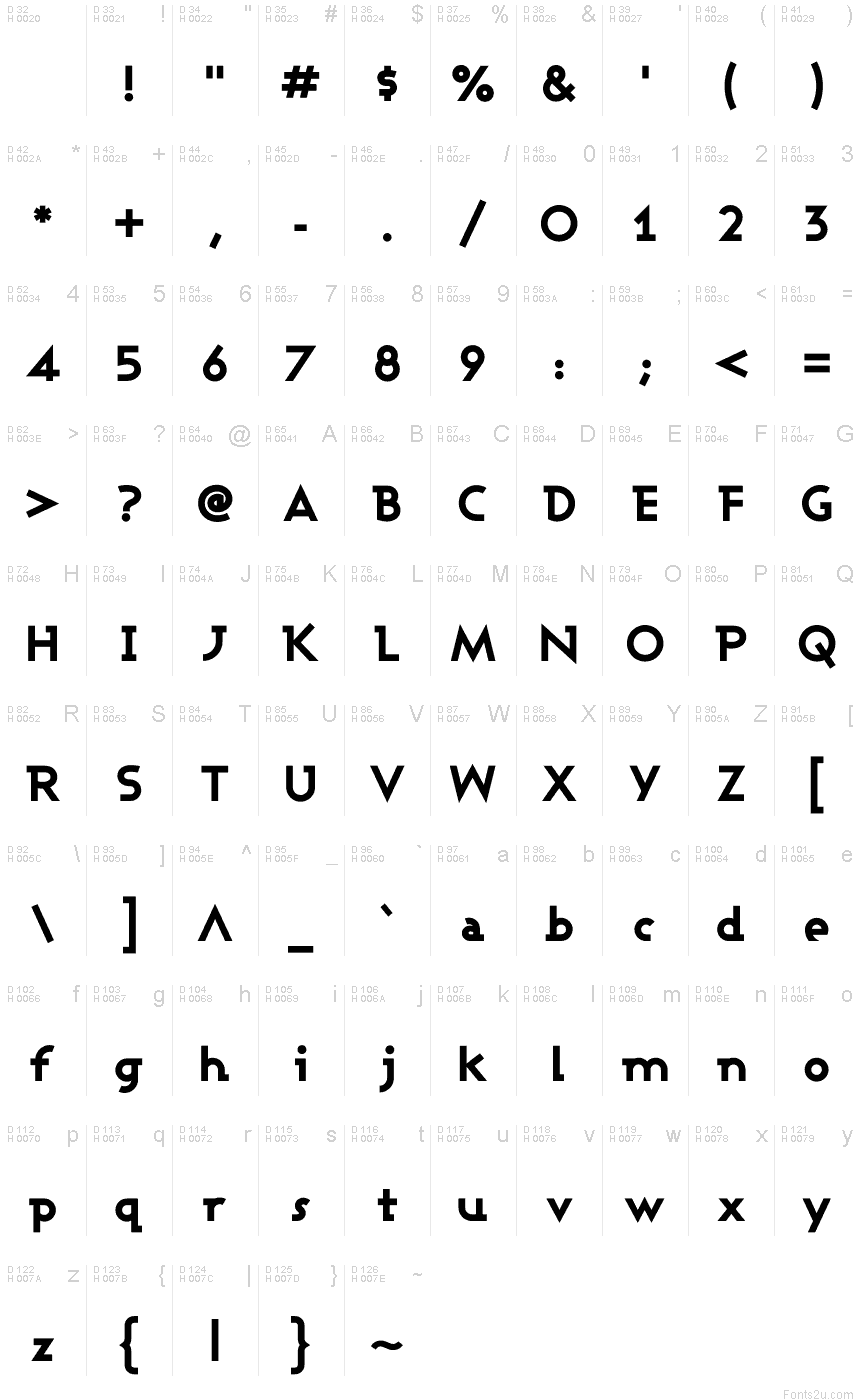
Ashby Extra Bold
Ashby Extra Bold autorstwa Robby'ego Woodarda to darmowy, retro font typu display o śmiałym, niemal rzeźbiarskim charakterze. Jego masywne linie, ostre przekątne i zaokrąglone światła wewnętrzne nadają mu zabawną dynamikę – w połowie geometryczną, a w połowie przypominającą ręcznie malowane szyldy. Litery są ciasno osadzone i pełne energii, przywodząc na myśl tytuły plakatów z lat 60., dzięki czemu każde słowo zyskuje wagę i osobowość.
Dzięki Ashby Extra Bold Twoje nagłówki natychmiast zyskują ten oldschoolowy sznyt, który pozostaje czytelny nawet na nowoczesnych ekranach. Ten darmowy krój świetnie sprawdzi się na plakatach, okładkach płyt, w brandingu, na opakowaniach, w grafikach eventowych i materiałach do mediów społecznościowych, które potrzebują mocnego akcentu vintage. Spróbuj połączyć Ashby Extra Bold z lekkim, neutralnym bezszeryfowym fontem w tekście głównym – najlepiej prezentuje się w dużym rozmiarze, gdzie jego charakter naprawdę ożywa.